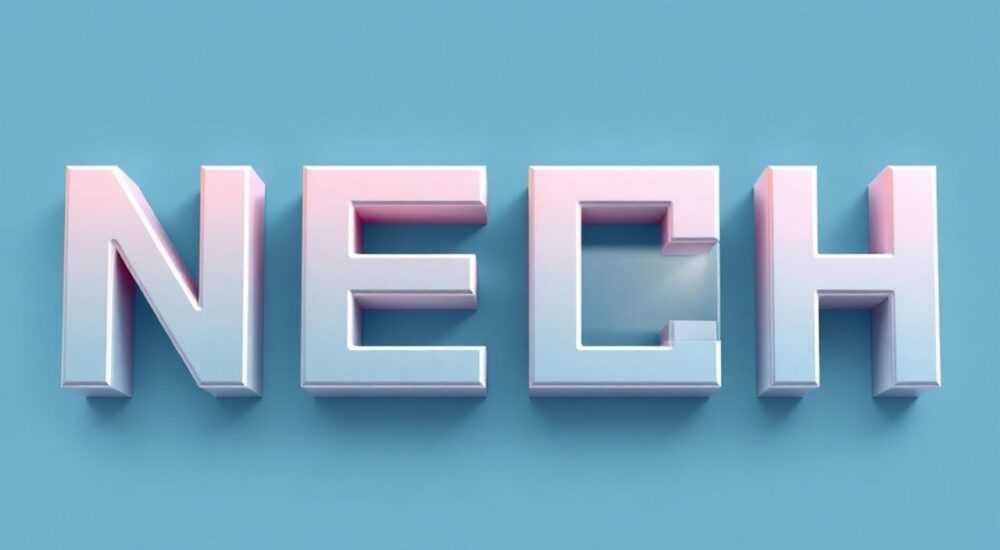
Как в фотошопе сделать объемный шрифт
В фотошопе объемный шрифт создается с помощью эффектов слоя, таких как Bevel & Emboss (Скос и тиснение), Contour (Контур) и Lighting Angle (Угол освещения). Ключевая рекомендация — использовать векторные текстовые слои и настраивать параметры экструзии через стили слоя для максимального контроля и качества.
Фотография, дизайн упаковки, рекламные баннеры — везде требуется выразительный текст. Объемный шрифт привлекает внимание, добавляет динамику и профессионализм. Adobe Photoshop предлагает мощные инструменты для создания 3D-текста без необходимости использовать специализированные 3D-редакторы. Технологии эволюционировали: если раньше приходилось имитировать глубину вручную, сегодня достаточно нескольких кликов, чтобы получить фотореалистичный результат. Однако многие пользователи до сих пор сталкиваются с проблемой — текст выглядит плоско или неестественно. Причина — неправильная настройка света, отсутствие деталей или игнорирование базовых принципов композиции.
Подготовка рабочего пространства и выбор шрифта
Перед тем как начать работу с объемным текстом, важно подготовить документ. Откройте Photoshop и создайте новый файл с подходящим разрешением. Для печати используйте 300 dpi, для веба — 72 dpi. Размер холста зависит от цели: баннер 1920×1080 пикселей, постер — A4 или больше. Убедитесь, что цветовой профиль соответствует задаче: RGB для экрана, CMYK для полиграфии.
Выбор шрифта напрямую влияет на восприятие объема. Жирные, геометрические шрифты (например, Impact, Bebas Neue, Oswald) лучше всего передают глубину. Избегайте слишком тонких или декоративных гарнитур — они теряют читаемость при наложении эффектов. Работайте с векторными текстовыми слоями: это позволяет масштабировать текст без потери качества и редактировать его в любой момент.
- Используйте горячую клавишу T для активации инструмента Text.
- Наберите нужный текст на новом слое.
- Не конвертируйте текст в растр без необходимости — это ограничит возможности редактирования.
Настройка фона и контекста
Фон влияет на восприятие объема. Темный фон подчеркивает светлый текст с бликами, светлый — делает акцент на тенях. Используйте градиенты, текстуры или изображения, чтобы добавить реалистичности. Например, объемный логотип на фотографии кирпичной стены будет смотреться естественнее, чем на сплошном цвете.
Базовая техника создания объемного текста
Создание объема начинается со стилей слоя. Щелкните правой кнопкой мыши по текстовому слою и выберите «Blending Options» (Параметры наложения). Здесь находится набор эффектов, которые формируют 3D-впечатление.
Ключевой эффект — Bevel & Emboss (Скос и тиснение). Он имитирует рельеф за счет светлых и темных граней. Настройте параметры:
- Style (Стиль): выберите «Inner Bevel» или «Emboss» в зависимости от желаемого эффекта.
- Technique (Метод): Smooth (плавный) или Chisel Hard (резкий) — второй вариант дает более четкие грани.
- Depth (Глубина): от 100% до 500%. Чем выше значение, тем выраженнее объем.
- Size (Размер): определяет ширину скоса. Начните с 5–10 пикселей и корректируйте по визуальному восприятию.
- Soften (Сглаживание): 0–2 px для легкого размытия краев, чтобы избежать «пластмассового» вида.
Настройка освещения и теней
Одна из главных причин, почему объемный текст выглядит неестественно — неправильный угол света. В разделе Bevel & Emboss найдите параметр Lighting Angle. Стандартный угол — 120°, но его можно менять в реальном времени. Убедитесь, что направление света согласуется с другими элементами композиции.
Добавьте Drop Shadow (Тень) — она усиливает ощущение парения или прижатия к поверхности. Настройте:
- Opacity: 50–75%
- Distance: 3–10 px (в зависимости от масштаба)
- Spread: 0–5%
- Size: 5–15 px
Расширенные эффекты и текстуры
Для достижения профессионального результата недостаточно базовых стилей. Добавьте детализацию с помощью дополнительных эффектов.
Контур и текстура поверхности
В разделе Bevel & Emboss активируйте Contour (Контур). Это кривая, которая управляет распределением света по грани. Выберите предустановленные варианты вроде «Ring Double» или «Cove Deep» — они создают сложные переходы, имитирующие металл или пластик.
Для еще большей реалистичности используйте Texture (Текстура). Загрузите паттерн (например, бетон, дерево, ткань) и настройте масштаб и глубину. Это особенно эффективно для стилизованных проектов — например, объемный текст на каменной стене.
Цвет и материал
Чтобы текст выглядел как металл, стекло или дерево, комбинируйте несколько эффектов:
- Gradient Overlay — наложение градиента для имитации бликов.